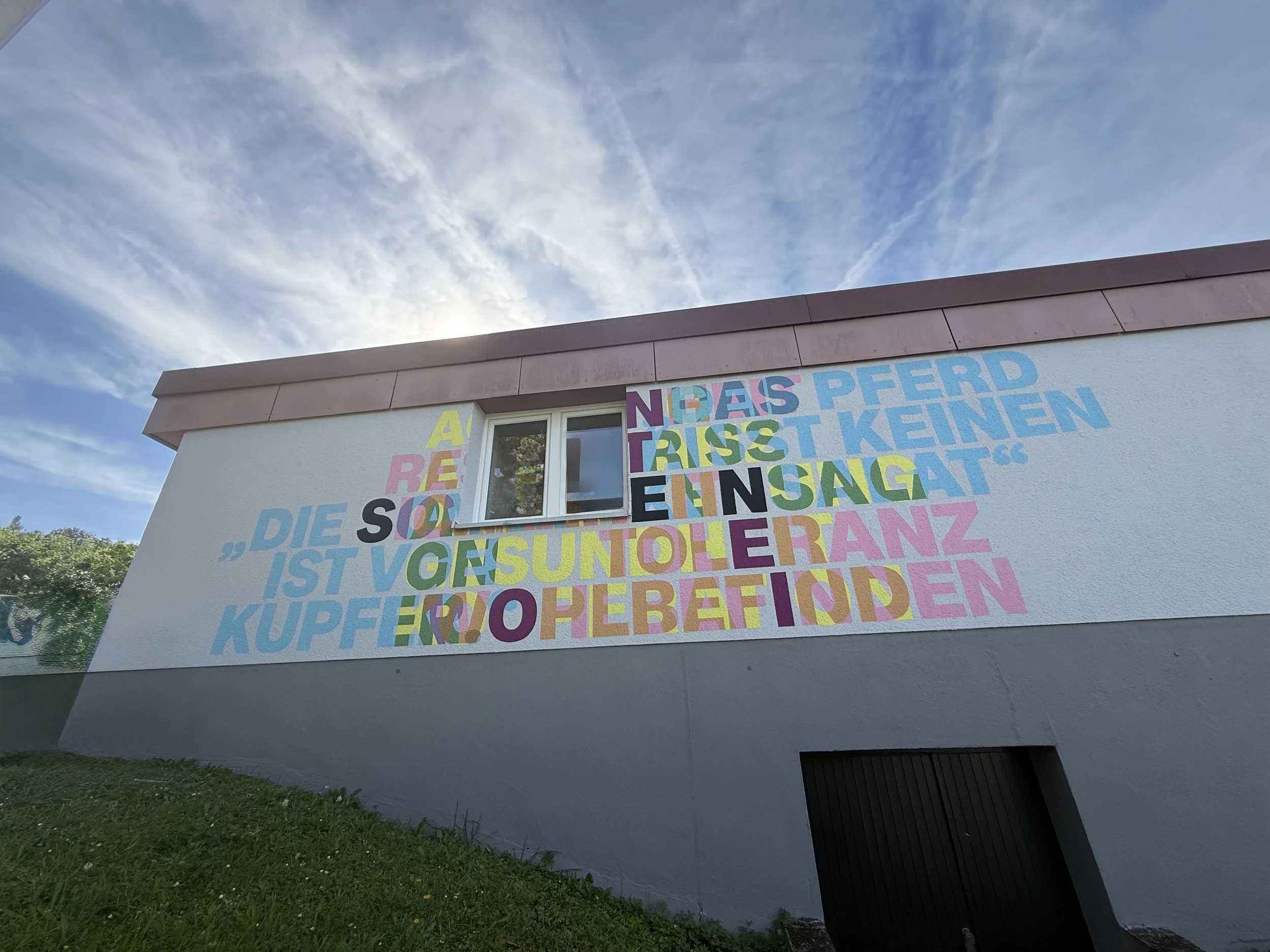
Outdoor-Museum der Poesie in Gelnhausen angekommen
Werk für das Outdoor-Museum der Poesie von Antonia Henschel im Eingangsbereich der Main-Kinzik-Kliniken in Gelnhausen
Die Stiftung Schrift und Bild mit ihrem Kurator Jörg Schmitz freut sich, dass nun die Arbeit von Antonia Henschel im Rahmen des Outdoor-Museums der Poesie auf der Kunstroute Main-Kinzig realisiert wurde.
In ihrem Entwurf für eine Fassade im Eingangsbereich der Main-Kinzig-Kliniken Gelnhausen hat Henschel einen berühmtes Zitat von Phillip Reis mit Begriffen aus dem Leitbild des Kreiskrankenhauses kombiniert. Die typografische Arbeit tritt visuell in den Dialog mit einer frühen Kunst-am-Bau-Installation (Urheber unbekannt) am benachbarten Facharztzentrum, die ebenfalls aus Buchstaben besteht.